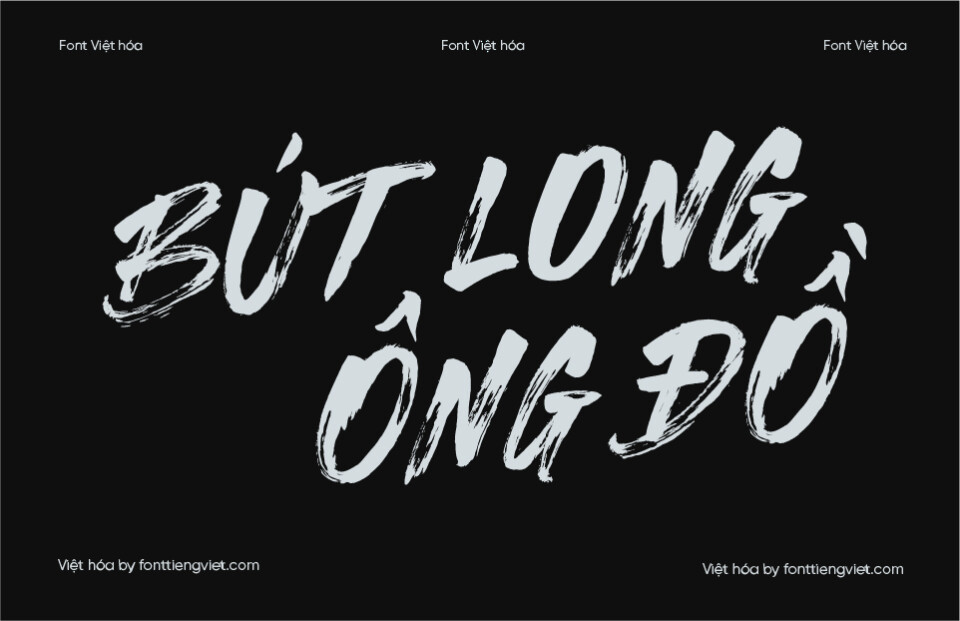
Trong thế giới thiết kế đồ họa hiện đại, việc lựa chọn một Font Chữ phù hợp có vai trò quyết định đến sự thành công và ấn tượng của một dự án. Đối với học sinh, sinh viên hay những người đang chuẩn bị cho các kỳ thi tốt nghiệp, việc tạo ra các ấn phẩm, poster, hay đồ án sáng tạo đòi hỏi một phong cách typography độc đáo. Đó chính là lý do Font Việt hóa 1FTV VIP Bridgers Brush đã trở thành từ khóa nóng được săn lùng. Đây không chỉ là một phông chữ; nó là một tuyên ngôn nghệ thuật, mang đến sự mạnh mẽ, phóng khoáng của nét cọ viết tay (brush script) nhưng vẫn đảm bảo tính chuyên nghiệp và khả năng hiển thị tiếng Việt hoàn hảo. Hãy cùng khám phá tại sao bộ font VIP này lại là sự bổ sung không thể thiếu cho kho tài nguyên sáng tạo của bạn, giúp nâng tầm mọi thiết kế học đường và cá nhân lên một đẳng cấp mới.
Khám Phá Nét Độc Đáo Của Font Việt hóa 1FTV VIP Bridgers Brush
Font Bridgers Brush ban đầu đã nổi tiếng với phong cách viết tay mô phỏng nét bút lông đầy năng lượng và cảm xúc. Phiên bản Font Việt hóa 1FTV VIP Bridgers Brush đã được tối ưu hóa một cách tỉ mỉ bởi đội ngũ chuyên nghiệp, đảm bảo rằng mọi ký tự tiếng Việt, từ các dấu câu, dấu thanh (sắc, huyền, hỏi, ngã, nặng) cho đến các chữ cái đặc biệt như ă, â, ê, ô, ơ, ư, đều được hiển thị một cách tự nhiên và hài hòa nhất. Sự tỉ mẩn trong việc Việt hóa này giúp người dùng tại Việt Nam hoàn toàn yên tâm khi áp dụng font vào các dự án đòi hỏi tính thẩm mỹ cao như thiết kế bìa sách, poster sự kiện trường học, hay các ấn phẩm kỷ yếu cuối cấp. Nét cọ mạnh mẽ, dứt khoát của Bridgers Brush tạo ra một hiệu ứng thị giác ấn tượng, rất phù hợp với các thông điệp truyền cảm hứng và sự kiện mang tính đột phá.
Điểm mạnh của font brush là khả năng truyền tải cảm xúc cá nhân. Khác biệt với các font serif hoặc sans-serif truyền thống, Bridgers Brush mang lại cảm giác chân thực, handmade, giúp tác phẩm của học sinh, sinh viên trở nên gần gũi và giàu cá tính hơn. Khi thiết kế backdrop cho lễ bế giảng, hay tiêu đề cho một bài báo tường, sự lựa chọn này sẽ giúp nội dung của bạn nổi bật hơn hẳn so với những phông chữ đã quá quen thuộc và đại trà.
Tại Sao Bridgers Brush Là Lựa Chọn Hoàn Hảo Cho Các Dự Án Học Đường?
Tối Ưu Cho Đồ Án Tốt Nghiệp và Bài Thuyết Trình
Giai đoạn cuối cấp học, đặc biệt là chuẩn bị cho kỳ thi tốt nghiệp THPT hay hoàn thành đồ án tốt nghiệp đại học, đòi hỏi sự đầu tư lớn vào cả nội dung lẫn hình thức trình bày. Font Việt hóa 1FTV VIP Bridgers Brush cung cấp một giải pháp typography mạnh mẽ cho phần tiêu đề hoặc các điểm nhấn quan trọng trong bài thuyết trình. Việc sử dụng font brush script một cách chiến lược có thể phá vỡ sự nhàm chán của các slide truyền thống, thu hút sự chú ý của giáo viên và hội đồng giám khảo ngay từ cái nhìn đầu tiên. Đồ án về thiết kế thời trang, kiến trúc, hay truyền thông sẽ đạt được hiệu quả thị giác vượt trội khi sử dụng phong cách font chữ này để thể hiện sự sáng tạo và khác biệt.
Hơn nữa, trong các hoạt động ngoại khóa hoặc dự án nhóm, việc tạo ra các poster quảng bá, áo đồng phục lớp, hay ấn phẩm kỷ niệm sẽ trở nên dễ dàng và chuyên nghiệp hơn. Sự sắc nét và tính nghệ thuật của font giúp nâng cao giá trị thương hiệu cá nhân hoặc tập thể học sinh, sinh viên. Đây là một công cụ giúp thế hệ trẻ tự tin thể hiện cá tính mạnh mẽ của mình qua ngôn ngữ thiết kế typography.
Tính Thẩm Mỹ Cao Và Khả Năng Việt Hóa Xuất Sắc
Việc font được Việt hóa ở phiên bản VIP (Very Important Person) đảm bảo rằng người dùng đang nhận được một sản phẩm chất lượng cao, đã được kiểm tra kỹ lưỡng về kerning (khoảng cách giữa các chữ cái) và legibility (khả năng đọc). Sự đồng nhất này là yếu tố quan trọng khi in ấn hoặc xuất bản các tài liệu chính thức của trường lớp. Nhiều font chữ nước ngoài khi cố gắng áp dụng tiếng Việt thường gặp lỗi về dấu câu hoặc sự mất cân đối, nhưng phiên bản Việt hóa này đã khắc phục hoàn toàn những nhược điểm đó, mang lại trải nghiệm sử dụng mượt mà và hiệu quả tối đa.
Việc sử dụng các font chất lượng cao, đặc biệt là những font được thiết kế với phong cách viết tay, đang là xu hướng typography toàn cầu. Việc trang bị cho mình bộ font như Bridgers Brush giúp học sinh và sinh viên tiếp cận gần hơn với tiêu chuẩn thiết kế quốc tế, làm giàu thêm kiến thức và kỹ năng thực hành thiết kế đồ họa của bản thân.
Các Ứng Dụng Phổ Biến của Font:
- Thiết kế logo và nhãn hiệu cá nhân.
- Tiêu đề cho video và vlog học tập.
- Thiết kế bìa và trang trí kỷ yếu lớp.
- Poster tuyên truyền các hoạt động xã hội, tình nguyện.
- Thiệp mời, thiệp chúc mừng tốt nghiệp.
Sử Dụng Font Việt hóa 1FTV VIP Bridgers Brush Một Cách Hiệu Quả và Đảm Bảo Bản Quyền
Để tối đa hóa hiệu quả của font, hãy thử nghiệm nó trên các phần mềm thiết kế chuyên nghiệp như Adobe Photoshop, Illustrator, hoặc Canva. Kết hợp Font Việt hóa 1FTV VIP Bridgers Brush với một font chữ sans-serif đơn giản cho phần nội dung chi tiết sẽ tạo ra sự cân bằng hoàn hảo, giúp thiết kế của bạn vừa nổi bật, vừa dễ đọc. Đây là một chiến lược typography đã được chứng minh là hiệu quả trong cả môi trường học thuật lẫn thương mại.
Tóm lại, Font Việt hóa 1FTV VIP Bridgers Brush là một tài sản vô giá đối với bất kỳ ai đang tìm kiếm sự khác biệt và đẳng cấp trong các dự án thiết kế của mình. Từ việc tạo ra các ấn phẩm học đường mang tính cá nhân cao cho đến việc chuẩn bị cho các bài thi và đồ án tốt nghiệp, font chữ này cung cấp sự kết hợp hoàn hảo giữa tính nghệ thuật của phong cách brush và độ chính xác của một bản Việt hóa chuyên nghiệp. Đừng ngần ngại bổ sung bộ Font Chữ độc đáo này vào bộ sưu tập của bạn để mở khóa tiềm năng sáng tạo không giới hạn. Hãy để Bridgers Brush giúp bạn kể câu chuyện của mình một cách mạnh mẽ và đầy cảm hứng nhất, đảm bảo mọi thông điệp của bạn đều để lại ấn tượng sâu sắc và khó quên.